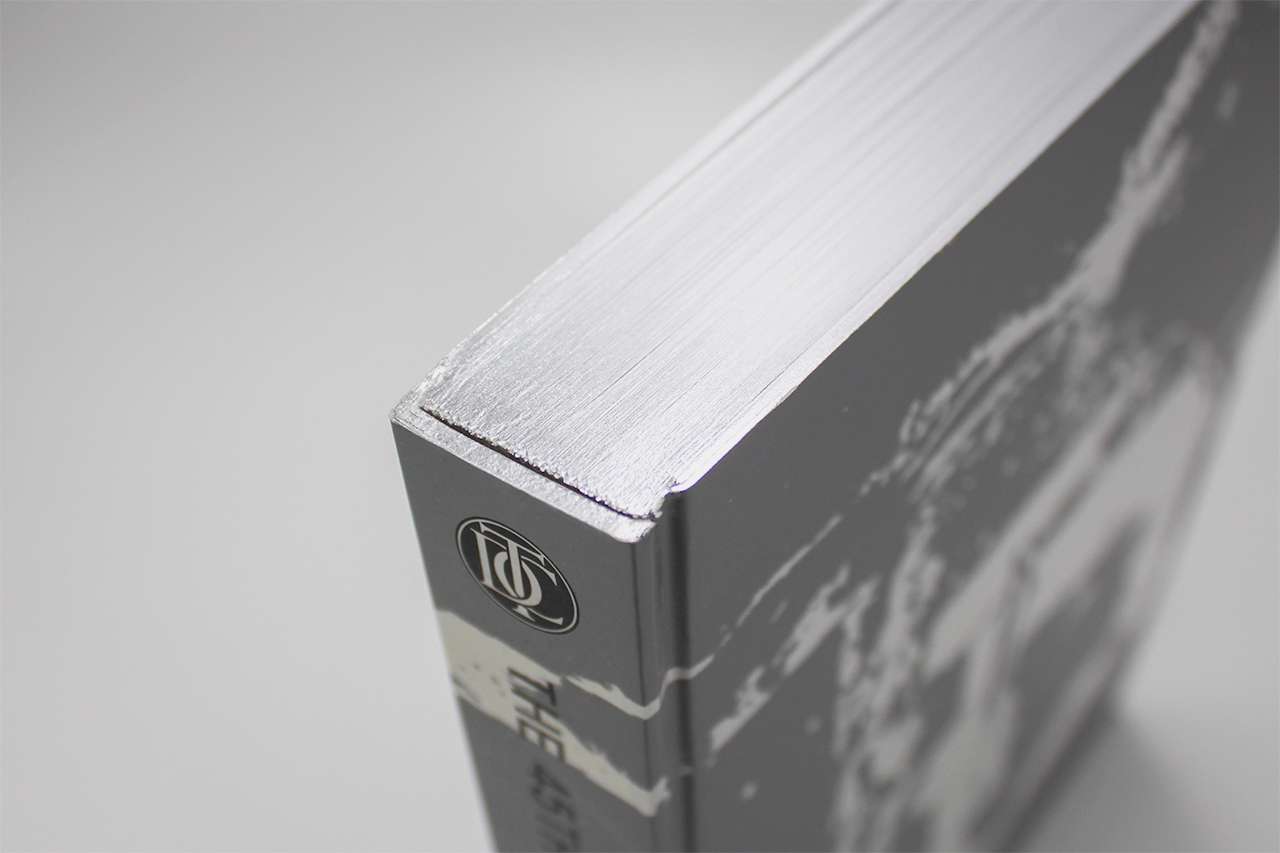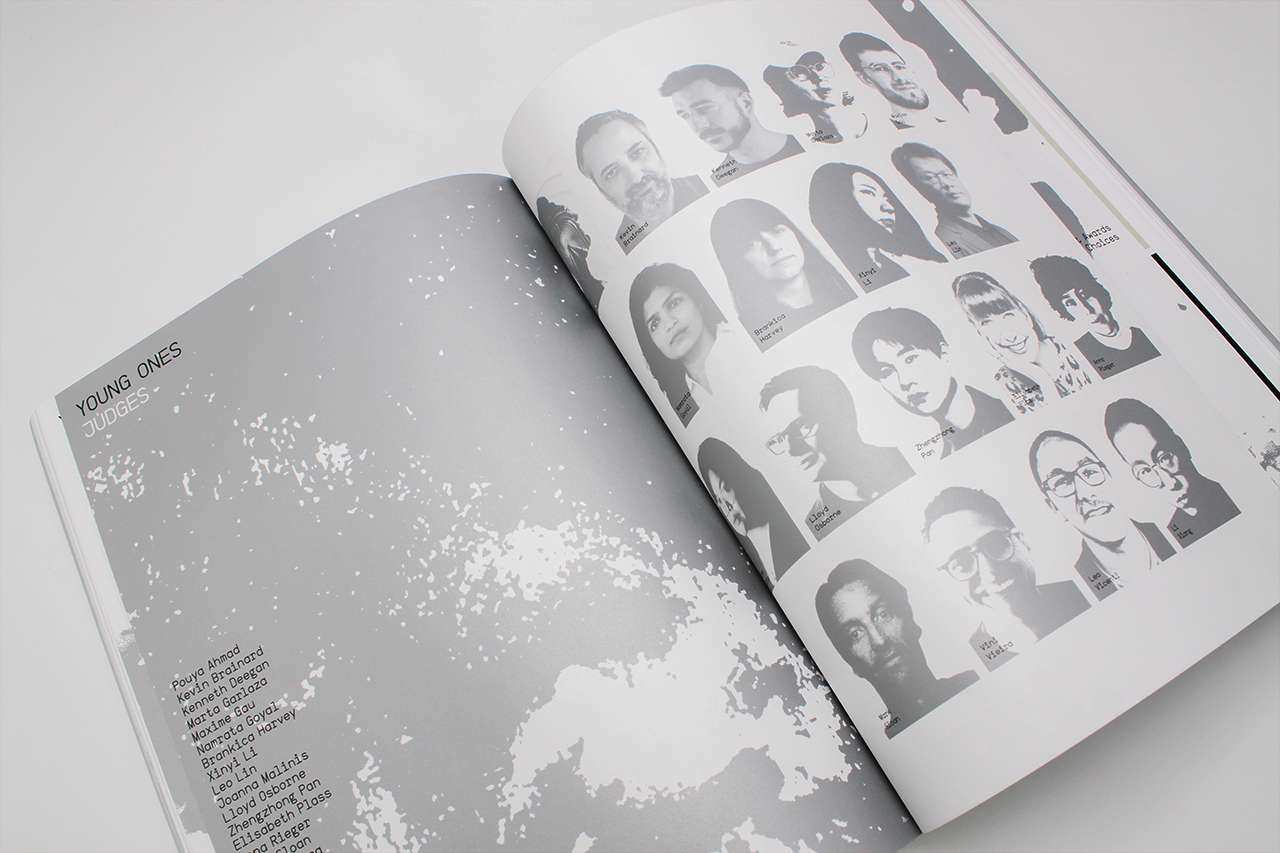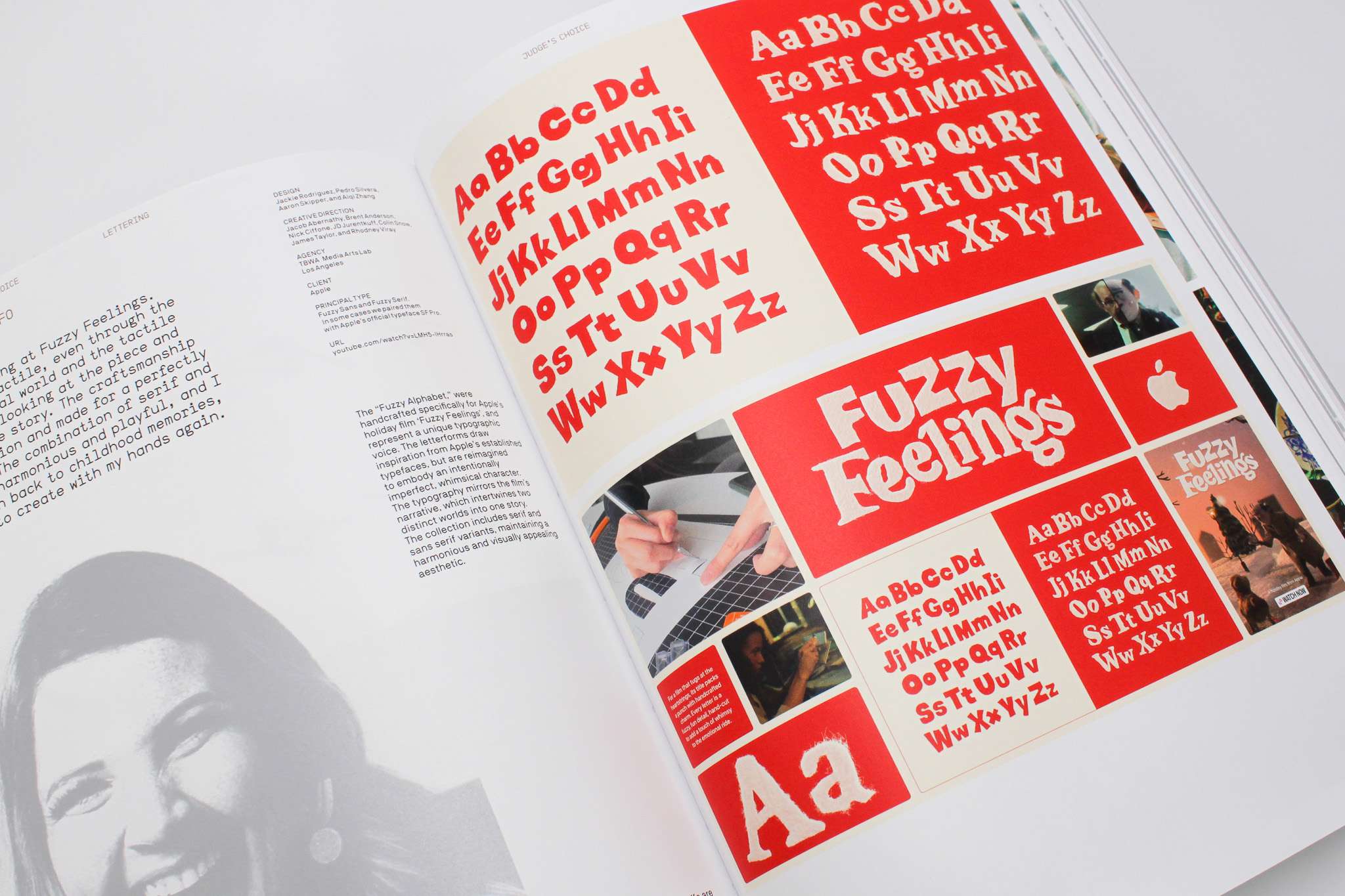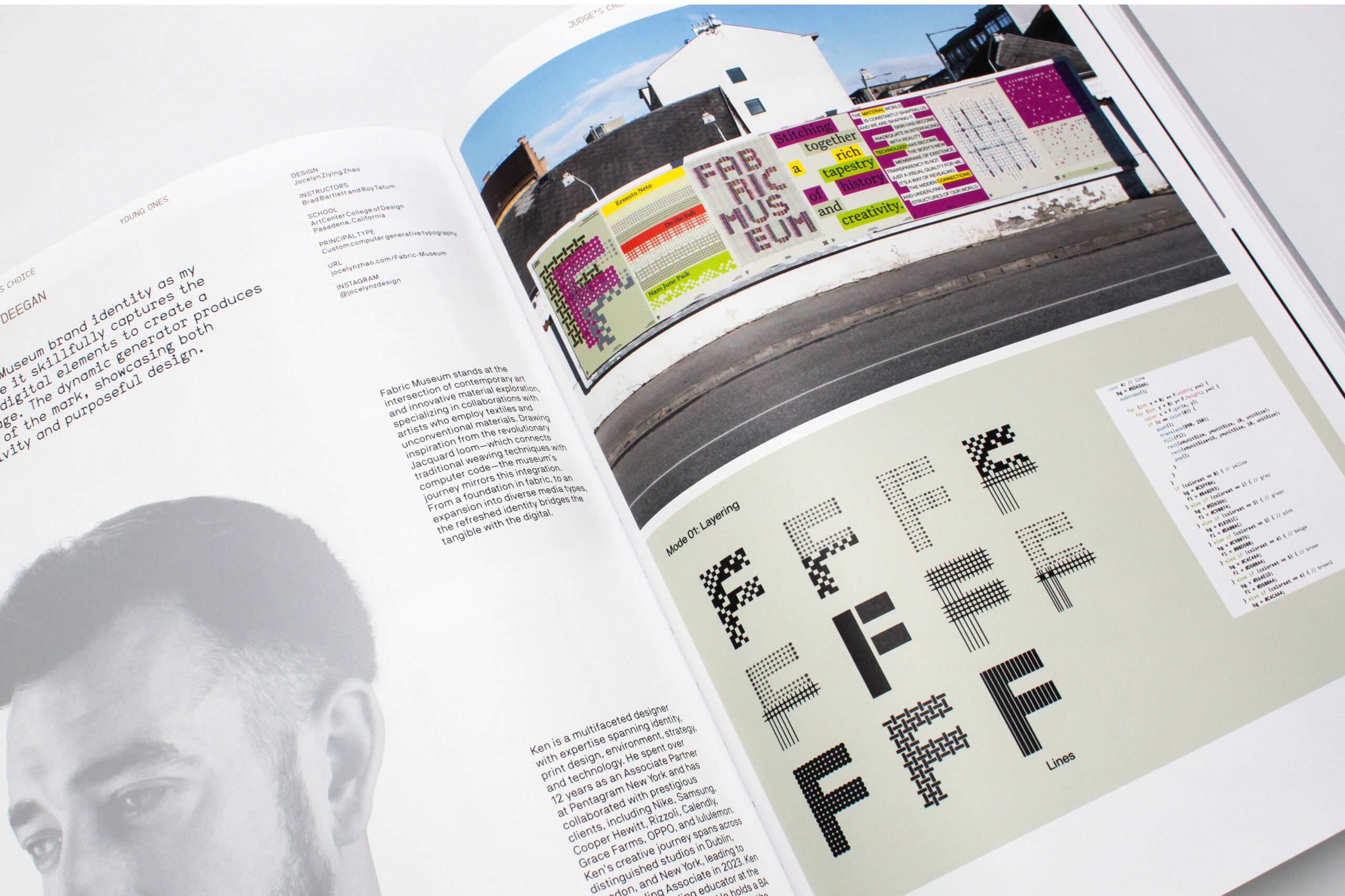
The World's Best Typography
Der Leckerbissen für Typografie-Afficionados! Was für den Sport Olympia, für den Fußball die WM, ist fürs Grafikdesign der TDC Wettbewerb des Type Directors Club of NY: Für diejenigen, die mitmachen, ist es die ultimative Herausforderung und im Falle eines Awards solider Karrierebaustein. Und für diejenigen, die zuschauen, sind die Siegerarbeiten Qualitäts-Messlatte, Intensiv-Inspiration und Trendradar.
Die ausgezeichneten Arbeiten sprühen vor Kreativ-Energie, loten Grenzen aus, spielen mit Regelbruch und Sehgewohnheiten und beeindrucken durch handwerkliche Exzellenz. Sie ziehen den zweiten Blick magisch an und bleiben im Kopf. Eine Hommage an die Power der visuellen Kommunikation!
Von kinetischer Typografie bis zum Motiondesign, vom Packaging bis zum Magazin, vom Corporate Design bis zur Kommunikation im Raum: Hier treten die Kreativsten der Welt gegeneinander an und die Siegerarbeiten sind atemberaubend.
Schaut man mehrere Jahrgänge der jeweils aufwändig gestalteten Jahrbücher hintereinander an, so zeichnen sich schnelle und langfristige Trends im Design ab und ein von Geschmacksfragen unabhängiges Qualitätsverständnis entwickelt sich. So wird das Jahrbuch »The World’s Best Typography« zum Sammlerstück und Zeitdokument.
In diesem Jahr sprüht es vor Farbenfreude und spielerischem Umgang mit Schrift. Und etwas Leichtigkeit und Optimismus kann dieses Jahr vertragen …
Zu Gestaltung und Ausstattung
Natürlich versuchen auch die jährlich wechselnden Buchgestalter:innen mit dem TDC Buch einen Meilenstein der Buchgestaltung zu setzen. In diesem Jahr hat Wolff Olins das große Los gezogen und setzt verschiedene Metallictöne als Sonderfarben ein. Das Buchobjekt ist eine Symphonie in Silber und strahlt im Buchregal.
The World’s Best Typography
The 45th Annual of the Type Directors Club 2024
Gestaltung: Wolff Olins Company
368 Seiten mit 203 preisgekrönten Arbeiten aus 41 Ländern, »awarded for Typographic Excellence«, sowie 37 neuen Fonts in der Kategorie »Best of Typedesign«
Durchgehend farbig gedruckt mit zusätzlichen Metallicfarben
Format 21 x 28,5 cm
Fadengehefteter, mattsilberner Festeinband mit dreiseitigem silbernen Blattschnitt